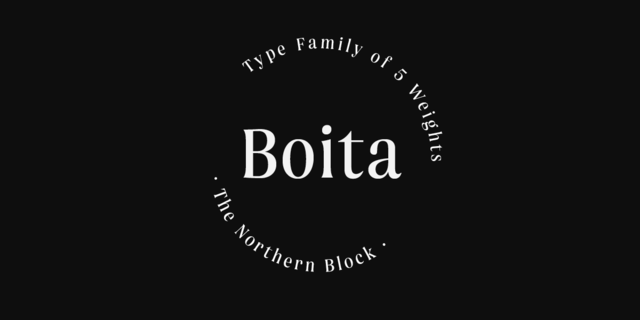
Boita – это элегантная акцидентная антиква. Гарнитура создана для сильного воздействия, она отличается большой высотой строчных, высокой контрастностью, уверенными формами и острыми засечками. Его сжатые пропорции позволяют привлекать внимание даже в условиях ограниченного пространства. Boita формирует на странице «гладкую, как бархат» текстуру, сохраняя ощущение отчетливой уверенности. Семейство поддерживает как латиницу, так и кириллицу. Шрифт разработала Мария Пигулевская в 2016 году. Botia™ является торговой маркой компании The Northern Block.
серьезный, устойчивый, статичный, традиционный, классический, аристократичный, салонный, торжественный, звонкий, благородный, качественный, культурный, острый, ностальгический, старомодный, богатый, консервативный, светский, серебристый, мастерский, роскошный, дорогой, эффектный, серебрянный, хрупкий, прозрачный, тонкий, элитный, модный, худой, джентльменский, пафосный, отборный, гладкий, гибкий, эстетичный, изящный, художественный, знаменитый, драгоценный, оригинальный, красивый, комильфо, сексуальный, старинный, исторический, солидный, гордый, выразительный, убедительный, важный, сильный, плотный, уверенный, крепкий, амбициозный, кинематографичный, экстравагантный, яркий, броский, заметный, твердый, авторитетный, настойчивый, громкий, тесный
отель, литература, вино, ресторан, комильфо, музей, роскошь, серебро, мода, часы, бутик, премиум, культура, искусство, художник, музыка, архитектура, скульптура, опера, поэзия, косметика, красота, алкоголь, коньяк, гостиница, шоколад, украшение, ювелир, драгоценности, сервировка, краска, чай, кофе, живопись, Библия, детектив, трофей, награда, закат, костюм, галстук, обед, ужин, кино, деньги, банк, банкнота, монета, концерт, виски, вечер, власть Стилистика: